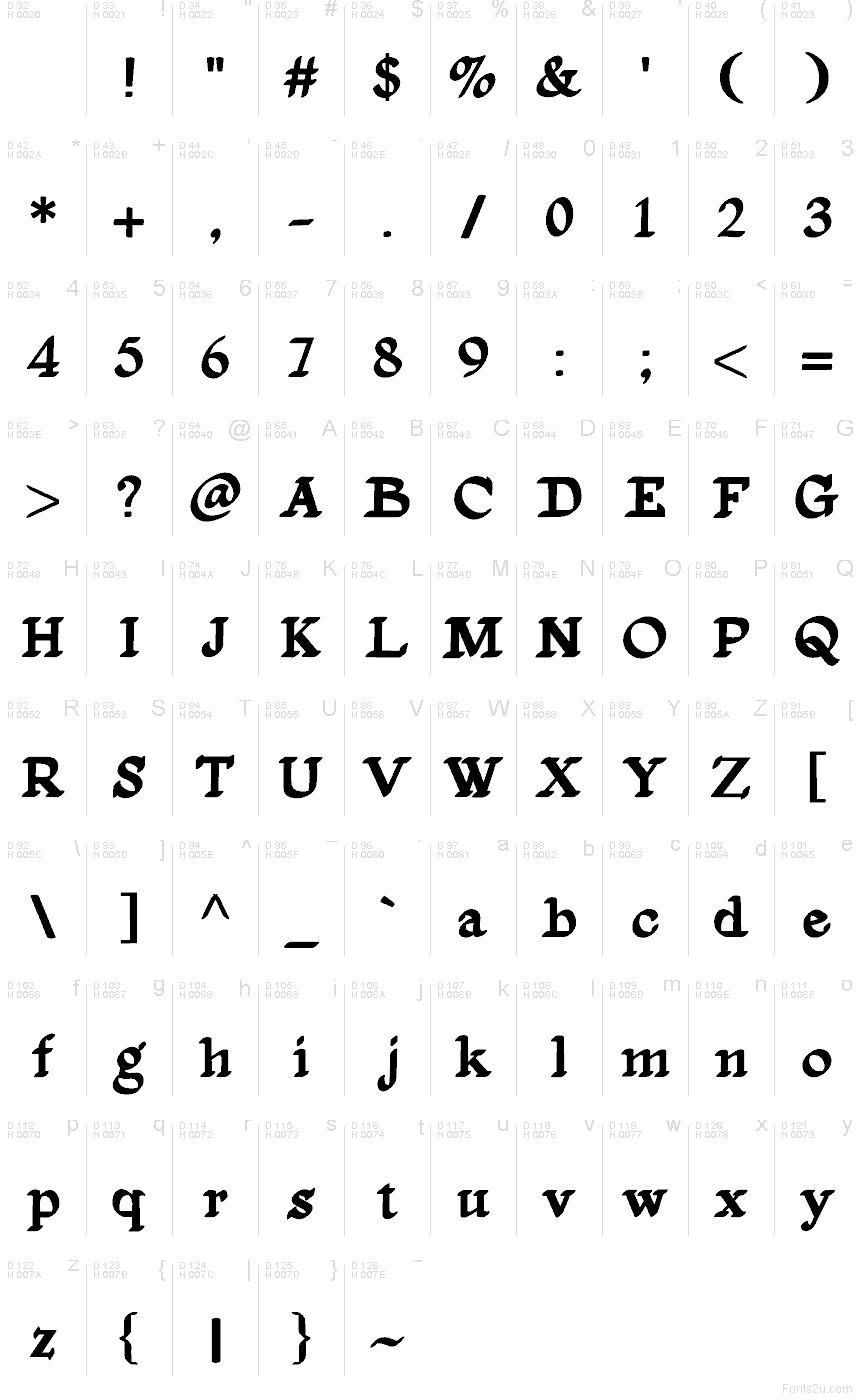
SLAB GRAB
Slab Grab, créée par Hello Good Studiov, est une police d'affichage slab serif gratuite dotée de larges empattements façonnés et de courbes fermes et creusées. Ses lettres adoptent un rythme gravé, presque typique de l'affiche, qui dégage une impression de robustesse sans sacrifier son élégance décorative.
Slab Grab est idéale pour les affiches, logos, packagings, pochettes d'albums et la signalétique courte, car ses formes slab conservent leur structure et confèrent aux mots une forte présence imprimée. Elle est également parfaite pour les couvertures de livres, les titres éditoriaux et les en-têtes de marque nécessitant une police aux détails slab marqués et à la tonalité d'affichage rétro distinctive.